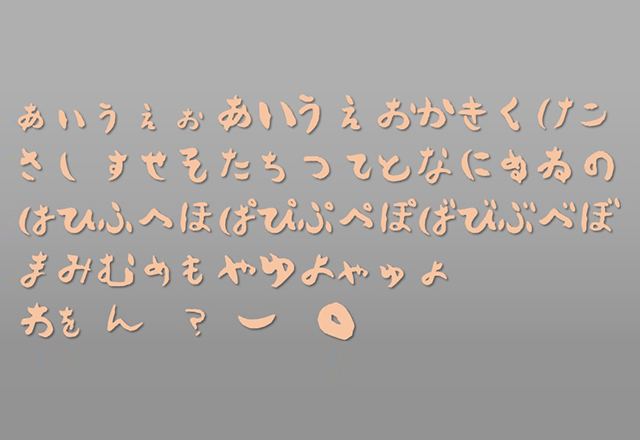
おくりびとフォント 2019.03.24 2016.12.01おくりびとフォントは、映画おくりびとをきっかけにはやったフォントです。ひらがなのみが入っています。ライセンス個人利用OKのフリートントです。商用利用は不可です。ダウンロードおくりびとフォント当サイトはフリーフォントの紹介サイトです。フォントを利用の際には、各サイトで最新の利用条件やライセンスを必ず確認してください。フォント情報ライセンス個人利用可カテゴリー日本語 > ユニークタグユニーク、手書き風、毛筆作者・シリーズフォント作成工房